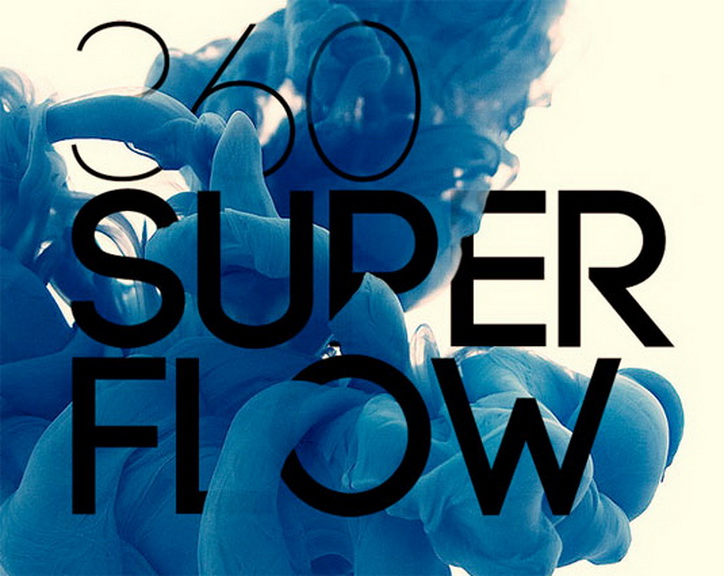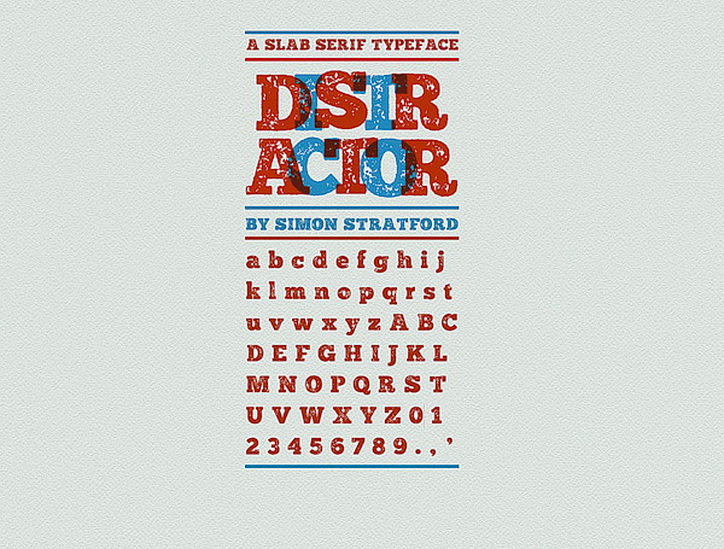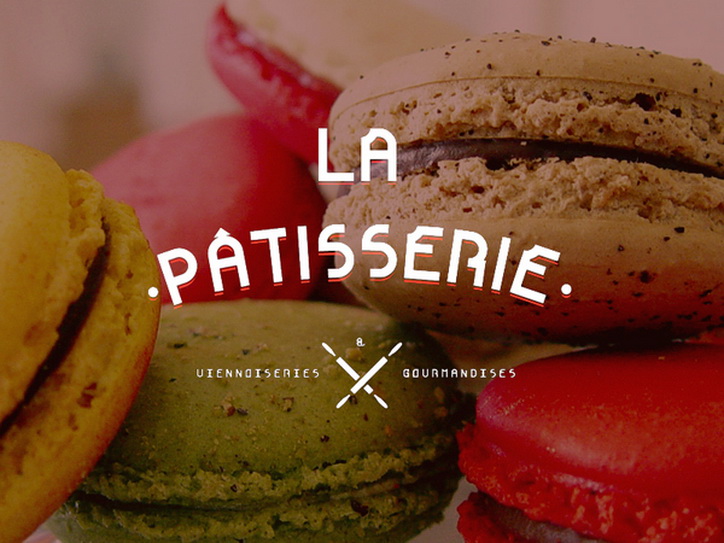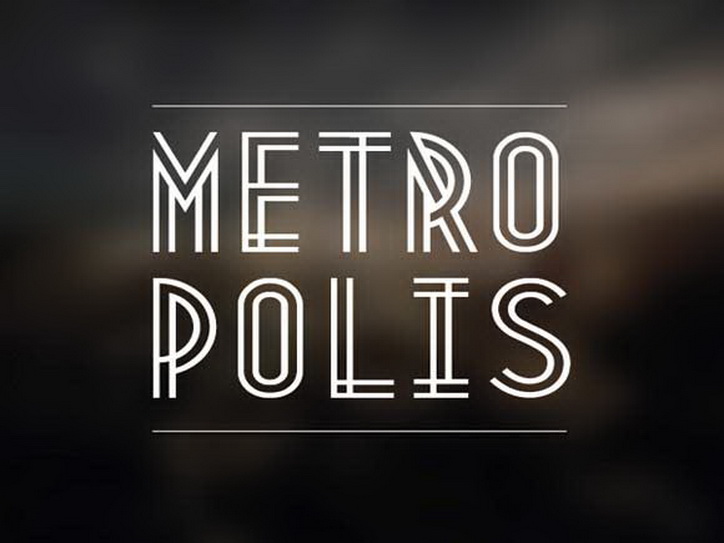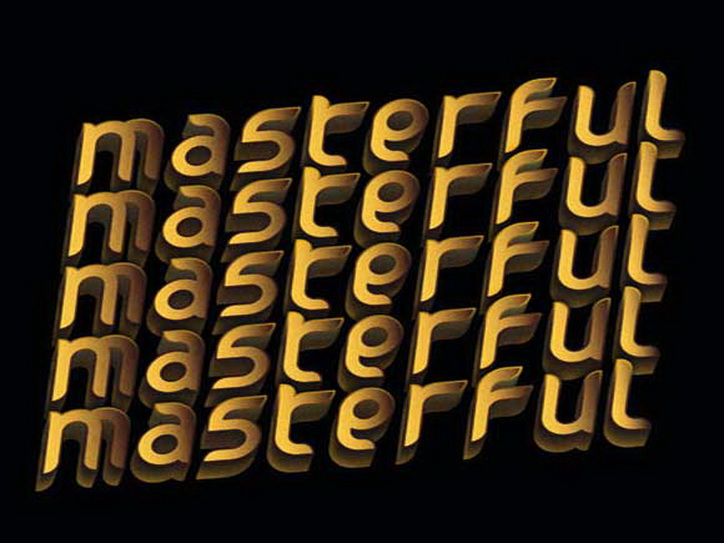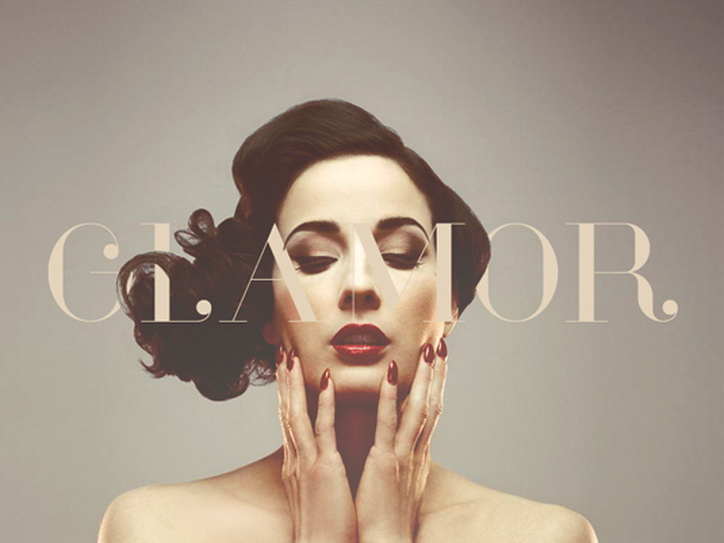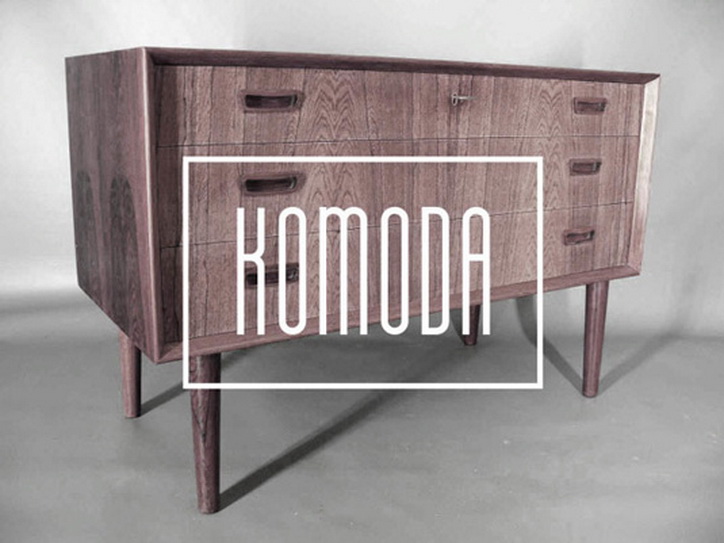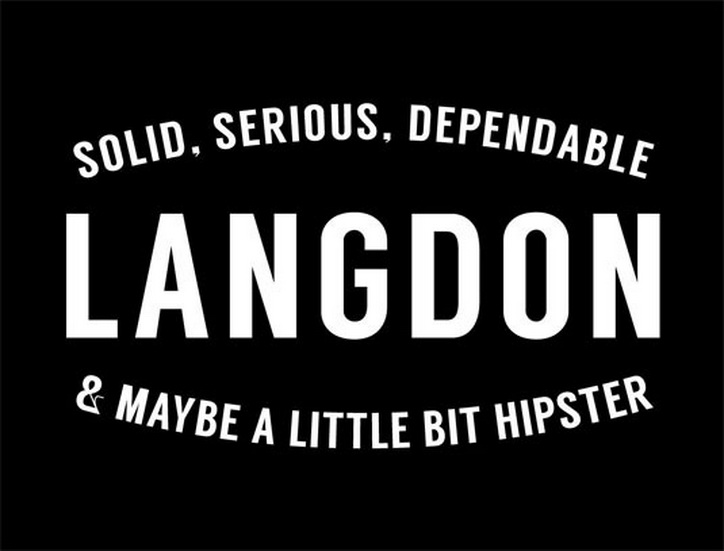
Tasarımcılar İçin En İyi 80+ Ücretsiz Font
Tasarımlarınızda görsel öğeler kadar önemli olan tipografi konusunda daha başarılı olmak istiyorsanız, ücretsiz yazı fontları ve güzel yazı fontları örnekleri size yardımcı olacaktır.
Birçok farklı amaçla kullanabileceğiniz modern, vintage ya da kalın yazı fontları gibi çeşitli tarzlarda yazı fontlarını ücretsiz olarak internetten rahatlıkla indirebilirsiniz. Ancak font denizi öyle büyük ki içinde kaybolmamak zor.
Farklı projeler için kullanabileceğiniz bu ücretsiz fontlar, vermek istediğiniz mesajı daha etkili kılabilir. Tasarımlarınıza esneklik kazandıracak Türkçe fontlar ve yabancı tüm fontları ücretsiz olarak bilgisayarınıza rahatlıkla indirebilirsiniz.
Ayrıca, estetik yazı fontları arasından seçiminizi yaparak tasarımlarınıza görsel kalite ve özgünlük katabilirsiniz.
Ücretsiz ve Popüler Yazı Fontları
Bariol
Bariol, modern ve okunaklı bir sans-serif fontudur. Hem web hem baskı projelerinde rahatlıkla kullanılabilir.
Baron
Baron, klasik tarzda bir serif fontudur. Başlık ve logo tasarımlarında etkileyici bir görünüm sunar.
Big Mouth
Big Mouth, kalın ve güçlü karaktere sahip bir fonttur. Başlık ve afiş tasarımlarında dikkat çekici bir tercih.
Bizon
Bizon, doğal ve rustik bir havası olan, güçlü karakterli bir yazı fontudur.
Big John
Big John, kalın ve modern bir sans-serif fontudur. Özellikle büyük puntolarda etkileyici görünür.
Building
Building, yapı ve mimari temalı projeler için tasarlanmış, net hatlara sahip bir fonttur.
Calender Plus
Calender Plus, sade ve okunaklı bir fonttur. Takvim ve planlama projelerinde ideal seçimdir.
Carton
Carton, çizgi film ve eğlenceli tasarımlar için tasarlanmış, kendine özgü karakteri olan bir fonttur.
Cassannet
Cassannet, ince çizgilere sahip modern bir serif fontudur. Zarif ve profesyonel projelerde tercih edilir.
RBN02
RBN02, modern ve geometrik yapısı ile dikkat çeken, çok amaçlı bir yazı fontudur.
Bohema
Bohema, bohem tarzını yansıtan, sanatsal ve özgün bir yazı tipi olarak kullanılır.
Comic Neue
Comic Neue, klasik comic fontunun modern ve daha okunabilir versiyonudur. Eğlenceli tasarımlarda tercih edilir.
Code Pro
Code Pro, teknik ve yazılım temalı projelerde kullanılmak üzere tasarlanmış sade bir yazı fontudur.
Cylburn
Cylburn, doğal ve organik tasarımlara uygun, el yazısı stilinde bir fonttur.
Delicate
Delicate, zarif ve ince yapıya sahip bir yazı fontudur. Düğün davetiyesi gibi hassas tasarımlar için uygundur.
Dense
Dense, sıkışık ve yoğun harf yapısı ile modern tasarımlar için güçlü bir font seçeneğidir.
Distractor
Distractor, dikkat çekici ve özgün karakteriyle başlık tasarımlarına hareket katar.
Dooodleista
Dooodleista, eğlenceli ve çizgi roman havası veren elle çizilmiş tarzda bir fonttur.
Fabrica
Fabrica, endüstriyel ve sağlam yapıya sahip, teknik projelerde sıkça tercih edilen bir fonttur.
Fail
Fail, deneysel tasarımlara uygun, sıra dışı ve dikkat çeken bir font türüdür.
Fairview
Fairview, sade ve profesyonel tasarımlar için uygun, okunabilirliği yüksek bir fonttur.
Farray
Farray, modern ve dengeli yapısıyla çok yönlü projelerde tercih edilen bir yazı fontudur.
Lovelo
Lovelo, geometrik ve kalın yapısıyla başlık ve afişlerde güçlü bir font seçeneğidir.
Nougatine
Nougatine, zarif çizgileri ve modern görünümü ile estetik projelerde sık kullanılan bir fonttur.
Bobber
Bobber, retro tarzı ve kalın harf yapısı ile dikkat çeken vintage bir yazı tipidir.
Sketchtik Light
Sketchtik Light, ince ve hafif yapısıyla minimal ve zarif tasarımlar için uygundur.
Metropolis
Metropolis, şehir temalı tasarımlar için modern ve dinamik bir font seçeneğidir.
Alphageometry
Alphageometry, geometrik şekillerle desteklenen, teknoloji odaklı tasarımlar için ideal bir fonttur.
League Script
League Script, zarif ve akıcı bir el yazısı fontudur. Davetiyeler ve tasarım projelerinde sıkça tercih edilir.
ChunkFive
ChunkFive, kalın ve dikkat çekici bir serif fontudur. Başlık ve afişlerde güçlü bir etki yaratır.
Forum
Forum, modern ve sade tasarımlar için uygun, okunabilirliği yüksek bir fonttur.
Futuracha
Futuracha, sanatsal ve dekoratif bir fonttur. Yaratıcı projelerde etkileyici sonuçlar verir.
Geared
Geared, endüstriyel temalı tasarımlar için uygun, mekanik görünümü olan bir yazı fontudur.
Glamor
Glamor, zarif ve şık tasarımlar için ideal olan, incelikli çizgilere sahip bir fonttur.
Habana
Habana, retro ve vintage tarzı sevenler için uygun, karakteristik bir fonttur.
Hay Maker
Hay Maker, güçlü ve dikkat çekici tasarımlar için ideal, kalın ve etkileyici bir fonttur.